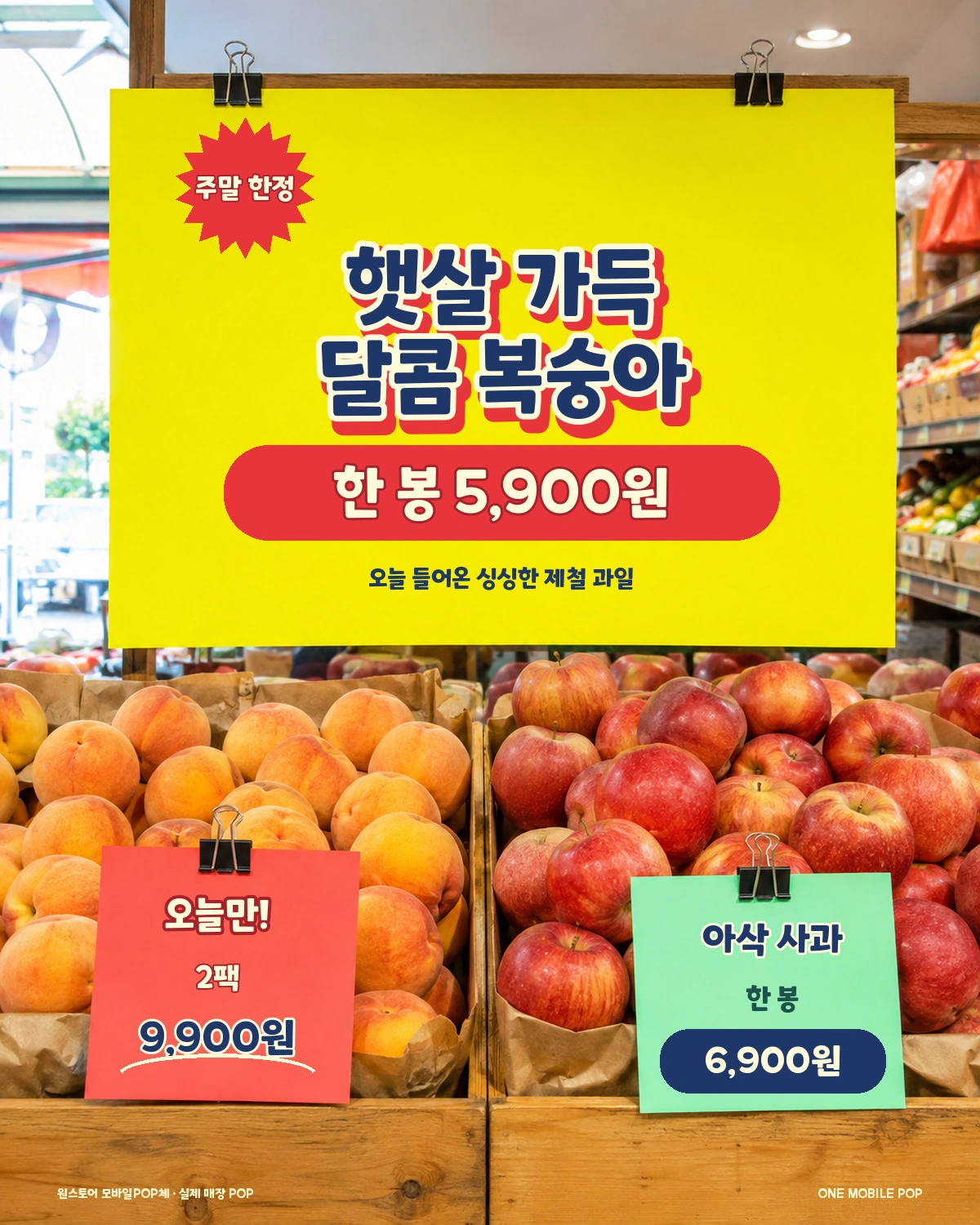
원스토어 모바일POP체 — (주)원스토어에서 배포하는 무료 폰트입니다. 톡톡 튀는 개성이 살아있는 POP 스타일 서체
원스토어가 폰트릭스와 함께 만든 전용 서체 다섯 벌 가운데 하나입니다. 배포 취지가 실용적입니다. 디자인과 문서, 개발 작업에서 겪는 고충을 덜어 주려고 무료로 푼 글꼴이라고 밝히고 있습니다.
제작사가 설명하는 성격은 이렇습니다. 원스토어만의 성격이 담긴 생동감 있는 손글씨체로 글자에 생기를 불어넣는 리드미컬한 라인과 요소를 담았다는 것입니다. 획의 굵기에 변화를 주어 글줄이 리듬을 타게 만든 것이 그 방법이고, 게임 캐릭터를 연상시키는 장난스러운 인상이 여기서 나옵니다. 실제로 원스토어 유튜브 자막에 쓰이고 있습니다.
자막이나 이벤트 배너, 캐주얼한 프로모션 문구에 맞습니다. 반대로 긴 본문이나 신뢰감이 먼저인 금융·의료 화면과는 성격이 맞지 않습니다. 라이선스에 주의할 점이 있습니다. 무료로 쓰고 BI와 CI, 임베딩까지 가능하지만 폰트 자체의 수정과 재배포는 금지됩니다.